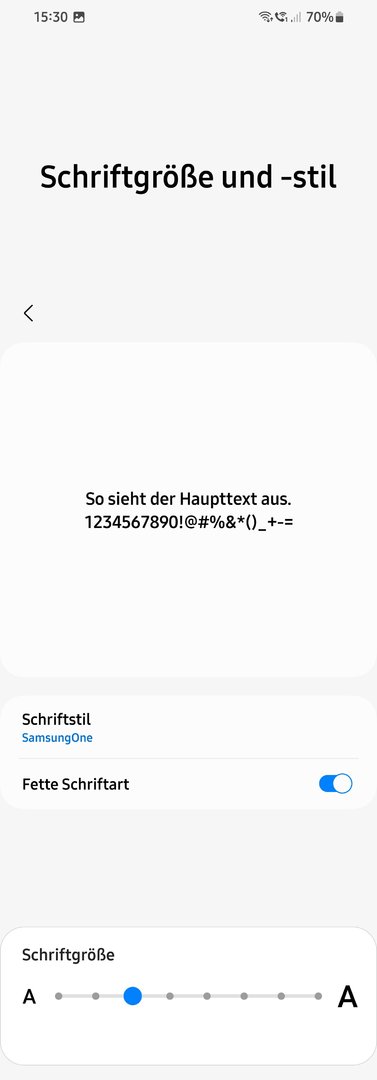
Welche Schriftart verwendet Ihr auf dem Galaxy S22 Ultra?
Hi. Kannst Du mir den Namen, der Schriftart veraten 😉
Die Schriftart heißt ZFrememberL. Ich habe sie im Samsung-Store gekauft.
Ja, das ist sie.
Es gibt tatsächlich Leute, die Anzeigeschriften für ihr Handy kaufen!? 🤔
Ja, offensichtlich.
Ist doch kein Problem.
Bei mir: SamsungOne als fette Schriftart.
Ich nutze die normale voreingestellte Schrift und käme auch gar nicht auf die Idee sie ändern zu wollen🤷😄
Definitiv kein Problem. Ich hätte nur nicht gedacht, dass wirklich jemand Geld dafür ausgibt.
Mein Ziel ist, die Schrift möglichst einfach und schnell erfassen zu können. Dem wird die Standardschrift vollkommen gerecht. Das muss ich nicht noch irgendwie verkomplizieren. 😁
Man ändert hier und da die Farben, manchmal das Hintergrundbild oder Theme und manchmal eben die Schrift. Alles nicht zwingend nötig, aber ich optimiere und verschönere es für mich. Bei meiner jetzigen Schriftart bin ich schon länger und sie gefällt einfach etwas besser, als die Standard Schriftart. Kompliziert ist es überhaupt nicht und 1,56 Euro finde ich nicht besonders teuer.
Dito, nutze ich exakt genauso. Versuche aber einen sauberen Port von Google Literata oder Amazon Bookerly zu finden. Müssten sich theoretisch gut lesen auf mobilen Displays. Oder es ist nur eine windige Idee ;)
Ich mag es einfach nicht eine Standard Schriftart verwenden zu müssen. Ich nutze schon sehr lange die Tetra Flipfont, weil sie der Huawei Porsche, Design sehr ähnlich sieht und die mochte ich auch schon, als ich noch Huawei nutzte.
Also ich habe zwar ein Samsung Galaxy S20 FE 5G aber da kann man die Schriftarten ja auch anpassen.
Ich benutze da tatsächlich eine etwas verspieltere Schriftart seit gestern. 😁
Diese hier: CC Glitter Girl Regular Latin FlipFont - Apps im Galaxy Store
Und ich liebe sie tatsächlich.
Lässt sich auch alles sehr gut ablesen.
Ich finde diese ganz nett. Leicht, aber nicht zu verspielt:
Rt OperaRose™ Latin Flipfont - Apps im Galaxy Store
Was ich bei Schriftarten immer etwas schade finde ist das sie nicht überall aktiv sind. Hier im edge Browser gerade z. B. nicht oder im Google Discover.
Mit dieser Schriftart fällt es aber nicht so dolle auf da es nicht so ein härter Übergang ist - super :)
@LDNV im Samsung-Browser sieht man die Änderungen👍
Schriftart Schoko Cookie. Seit dem S3 nutze ich die
Die Schriftart Schoko-Cooky nutze ich gefühlt schon seit dem Note 1.
Kann mich zumindest nicht dran erinnern jemals als eine andere genutzt zu haben seit ich Samsunghandys habe.